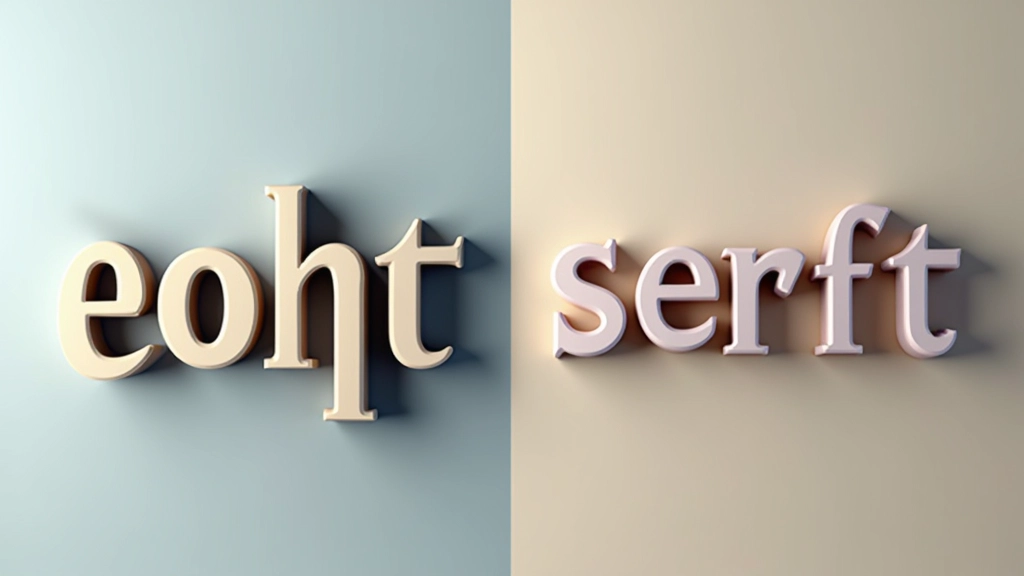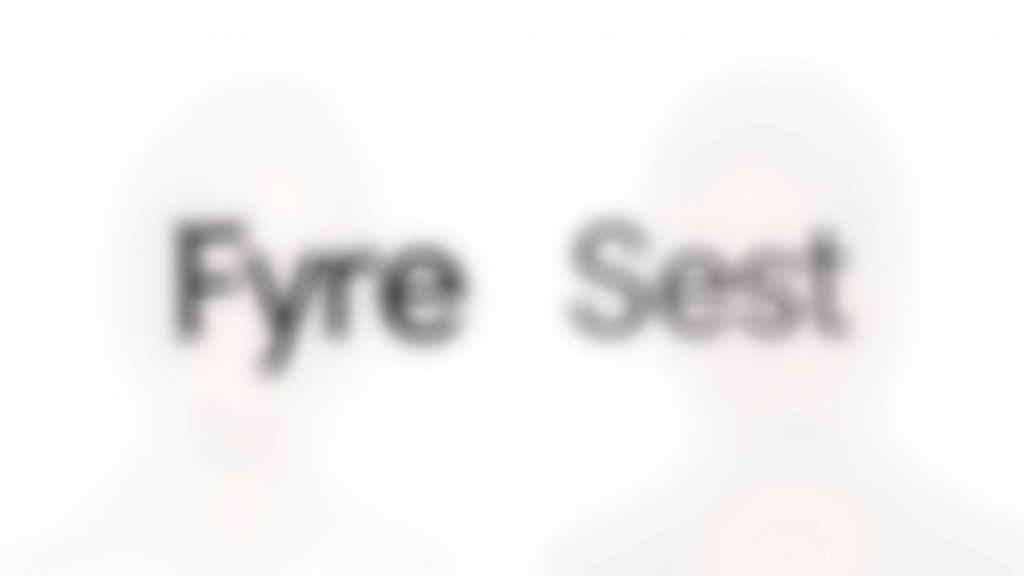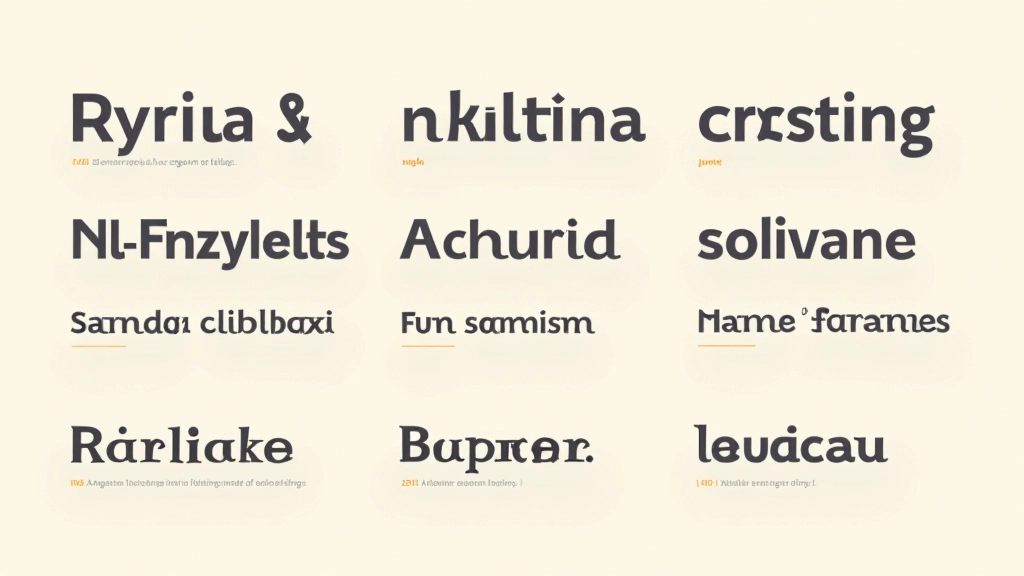
Entender o Contraste de Peso
O contraste de peso é o aspecto mais óbvio, mas também o mais fácil de estragar. Quando emparelhas uma fonte pesada com uma leve, esperas ver uma clara separação. Mas quando ambas se movem simultaneamente, esse contraste pode desaparecer.
Por exemplo, uma Sans-Serif Bold a 200ms pode parecer mais lenta do que uma Light a 300ms. O movimento psicológico interfere com a perceção visual do peso. É por isso que os designers experientes testam pares em velocidades diferentes. Eles não apenas olham — veem em ação.
- Testa o par a 500ms, 1s, e 2s de duração
- Nota como o peso visual muda com a velocidade
- Ajusta o tamanho base se necessário
Proporção e Largura de Caracteres
Além do peso, a largura do caractere (ou “set width”) é crucial. Uma fonte condensada emparelhada com uma fonte normal cria tensão visual. Isso pode ser intencional — ótimo para títulos — ou acidental — terrível para legibilidade.
Em movimento, essa tensão amplifica-se. Se uma fonte entra condensada enquanto a outra se expande, o efeito pode parecer descontrolado. Os melhores emparelhamentos mantêm proporções semelhantes, ou usam a diferença de forma muito deliberada.
Uma estratégia prática: mantém ambas as fontes no intervalo normal a largo. Reserva condensadas apenas se a animação o exigir especificamente.
Serifa vs. Sem-Serifa em Movimento
É um clássico: combinar uma fonte com serifa com uma sem-serifa. Funciona em papel, e pode funcionar em movimento — se fores estratégico.
A serifa adiciona detalhe. Quando essa fonte se move rapidamente, os detalhes podem desaparecer em resoluções mais baixas. Uma sem-serifa mantém-se legível a qualquer velocidade. É por isso que muitos designers usam sem-serifa para o texto em movimento rápido e serifa para poses estáticas ou entradas/saídas lentas.
Não evites este emparelhamento — apenas sê consciente do tamanho mínimo e da velocidade da animação. Testa sempre em contexto real.
Teste Prático: A Abordagem dos 5 Pares
Aqui está uma técnica que funciona. Escolhe 5 pares de fontes que te interessam. Não escolhas aleatoriamente — tem uma razão para cada par. Depois, cria um pequeno teste de animação para cada um.
Anima a primeira fonte a entrar, depois a segunda. Observa como se comportam juntas. Nota qual par sente natural e qual sente forçado. Aos 30 minutos, terás uma compreensão clara de quais funcionam.
Este processo força-te a ser intencional. Não escolhes fontes porque parecem bonitas isoladamente — escolhes porque funcionam em dueto.
Resumo: As Regras Não Escritas
O emparelhamento de fontes para movimento não segue regras rígidas. Não há uma fórmula “sempre funciona”. O que existe é um conjunto de princípios: contraste claro, proporções coerentes, teste rigoroso, e bom senso visual.
Comece com pares que já conhece. Uma Helvetica com uma Georgia. Uma Inter com uma Playfair Display. Testa-os em movimento. Vê o que sente bem. Depois, construa a partir daí.
A tipografia cinética é sobre comunicação através do tempo. Os pares de fontes que escolhes determinam como essa mensagem é recebida. Escolhe com cuidado, testa com frequência, e confia no que vês em movimento — não no que vês imóvel.